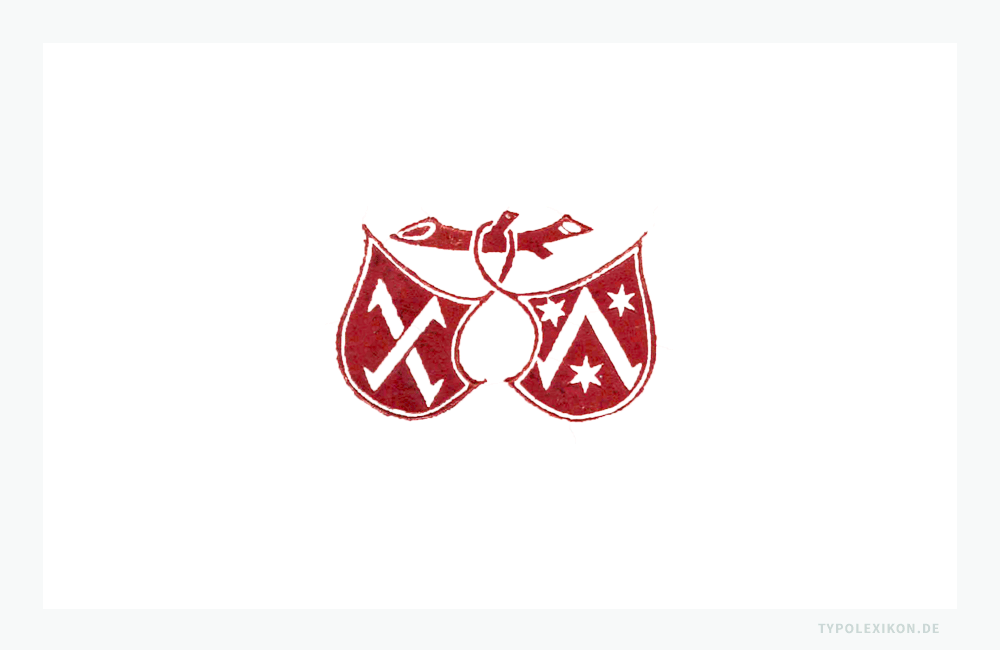
Fust, Johann
Mainzer Kaufmann, Geldverleiher und Fürsprech (Fürsprecher, Advokat), ab circa 1454 Typograf und Verleger in Mainz. Geboren um 1400 in Mainz, gestorben 1466  in Paris. Von ungefähr 1448 bis 1454 Geldgeber, Geschäftspartner und Gläubiger von Johannes Gutenberg (um 1400–1468), dem Erfinder der Typografie, Mitbegründer der Frankfurter Buchmesse. Die von Gutenberg übernommene und ab 1456 umbenannte »Fust-Schöffer´sche Offizin« gilt als die Keimzelle der Typografie. Alternative Schreibweisen seines Namens sind »Johannes Fust« und »Joannes Faustus«.
Johann Fust war der Sohn von Nicolaus Fust (um 1374–1444), der von 1438 bis 1441 Richter und ab 1444 Ratsmitglied in Mainz war. Sein Bruder Jacob Fust war Bürgermeister von Mainz. Zusammen mit seiner Frau Margarete, geborene Cuhn (um 1412–1472), hatte Johann Fust zwei Kinder, Christine (spätere Schöffer) und Johannes. 1)
Faksimile einer 42-zeiligen Gutenberg-Bibel. Original gedruckt von Johannes Gutenberg in Mainz um 1455. Quelle: New York Public Library, 2009.
Ab etwa 1448 (oder 1450?) investierte Johann Fust Geld in Gutenbergs Offizin im Humbrechthof in Mainz und finanzierte somit die kostenintensive Erstausgabe der Gutenberg-Bibel.
Nach einem Rechtsstreit in Mainz mit Johannes Gutenberg – Fust wollte das Gewinn bringende Geschäft mit seinem geschäftstüchtigen Schwiegersohn Peter Schöffer (um 1425/1430–1502/1503) fortsetzen und forderte deshalb skrupellos seinen Kredit von 1.600 Gulden (damaliger Gegenwert von drei Mainzer Bürgerhäusern) samt Zins und Zinseszins (etwas über 2.000 Gulden) zurück – ging Gutenbergs Offizin im Humbrechthof Ende 1454 in der Fust-Schöffer´schen Offizin auf. 2)
Der Kalligraf und Typograf Peter Schöffer, ehemaliger Geselle und Meisterschüler von Johannes Gutenberg, war nach dem gewonnen Prozess gegen Gutenberg – in dem er als Zeuge gegen Gutenberg aussagte – ab 1454 Werkstattleiter, Partner und nach seiner Heirat mit Johann Fusts Tochter Christina und dem Erbverzicht des Fustsohnes Johannes ab 1476 Alleineigentümer der Offizin.
Reproduktion des Druckerzeichens der Fust-Schöffer´sche Offizin um 1471/1477 des Mainzer Prototypografen Peter Schöffer (um 1425/1430–1502/1503). Es gilt als das älteste europäische Druckersignet: Zwei miteinander verbundene, an einem Ast hängende Wappenschilde, die mit stilisierten Winkelhaken und Sternen verziert sind.
Nach der gewaltsamen Einnahme von Mainz in der Nacht vom 28. Oktober 1462 durch die Truppen des von Papst und Kaiser favorisierten Kurfürsten und Erzbischofs von Mainz Adolf von Nassau (um 1423–1475), musste die Offizin im Humbrechthof in Windeseile aufgegeben werden, da Johann Fust und Peter Schöffer Günstlinge des nunmehr abgesetzten Kurfürsten, Erzkanzlers und Erzbischofs Diether von Isenburg (1412–1482) gewesen waren. Viele Mitarbeiter der Fust-Schöffer´schen Offizin verließen bei dieser Gelegenheit Mainz und brachten so die »Deutsche Kunst« in andere europäische Städte und schlussendlich in die gesamte Welt (siehe Schriftgeschichte und Prototypografen).
In der Offizin von Fust und Schöffer entstanden bedeutende Inkunabeln. Hier erlernten u.a. auch die Prototypografen Arnold Pannartz (o.A.–um 1476), Conrad Sweynheym (o.A.–um 1474/1477) und Nicolas Jenson (1420–1480) die Kunst der Typografie, die geheime »Deutsche Kunst«.
Johann Fust gilt, neben Peter Schöffer und Konrad Henckis (Typograf und Buchhändler, vor 1470–nach 1481), 3)  als einer der Mitbegründer der Frankfurter Buchmesse, heute die größte internationale Buchmesse der Welt, die jährlich im Oktober auf dem Gelände der Messe Frankfurt stattfindet und seit 1949 im jetzigen Veranstaltungsformat vom Börsenverein des Deutschen Buchhandels kuratiert wird.
Johann Fust starb am 30. Oktober 1466 in Paris, vermutlich an der Pest.  4)  5)  6)  7)  8)
↑3 Anmerkung: Der Typograf und Buchhändler Konrad Henckis war ein Kompagnon von Peter Schöffer, Mitbegründer der Frankfurter Buchmesse und der spätere Mann der Witwe von Fust.